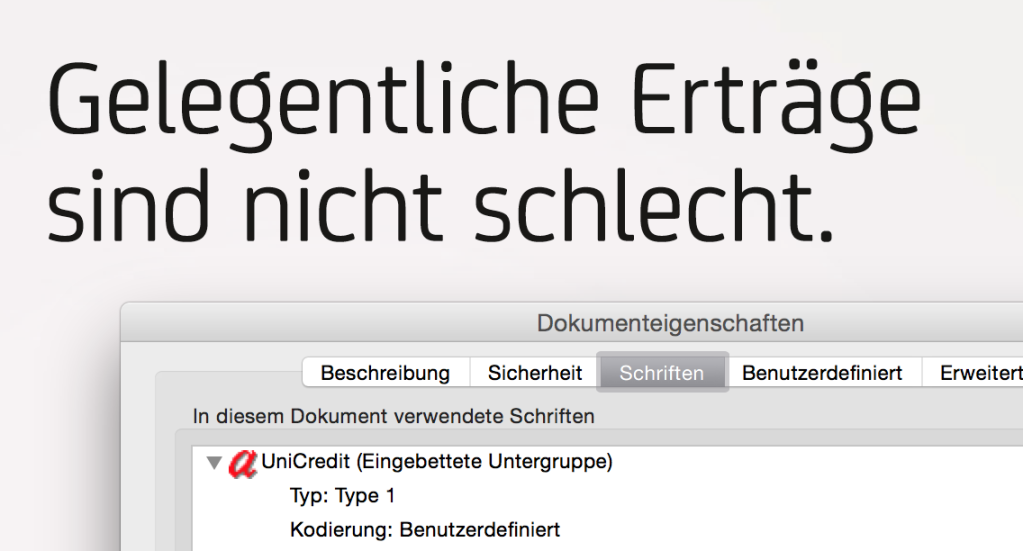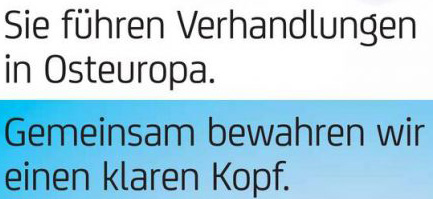
Schrift der Hypo-Vereinsbank-Anzeigen
kennt jemand von Euch die Schrift, die in den Anzeigen-Headlines Hypo-Vereinsbank zur Zeit verwendet wird? Ich lade mal ein Bild davon hoch...
#R::bert: die FS Joey hatte ich auch schon gefunden, aber das kleine g war nicht deckungsgleich...
#Martin: ich sehe gerade Martin, dass du die Logoschrift gemeint hast. Ich hatte ein Bild hochgeladen mit der Headlineschrift...
Nein, Ralf. Schau dir einfach den treffsicheren Tipp von R::bert an.
Doch, Jost. Die Schrift wurde exklusiv für die UniCredit/HV erstellt (und basiert höchstwahrscheinlich auf der Joey).
Fontsmith fertigt auch exklusive Corporate Fonts. Es ist daher gut möglich, dass sie in diesem Fall einen solchen gefertigt haben auf Basis der eigenen Schrift FS Joey. Und das wäre dann auch völlig in Ordnung.
Vielleicht noch ein Hinweis: Brauchst Du den Font um etwas für die Bank zu setzen, solltest Du Dich um die von Martin genannte Exklusivschrift bemühen um diese einzusetzen. Gefällt Dir aber einfach nur das Aussehen für ein völlig anderes Projekt, dann ist die FS Joey zu verwenden.